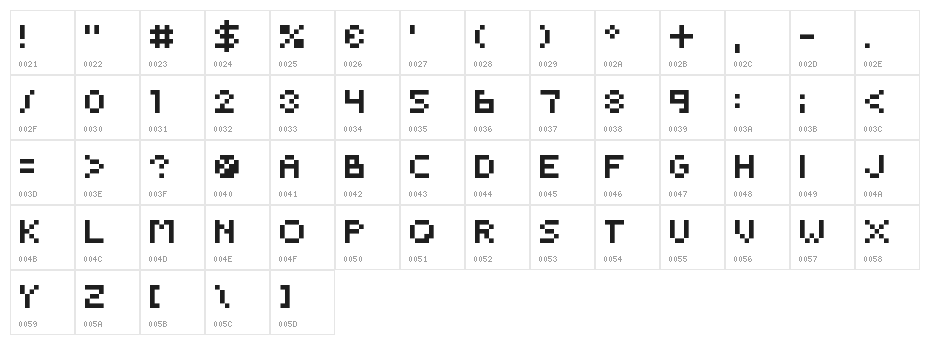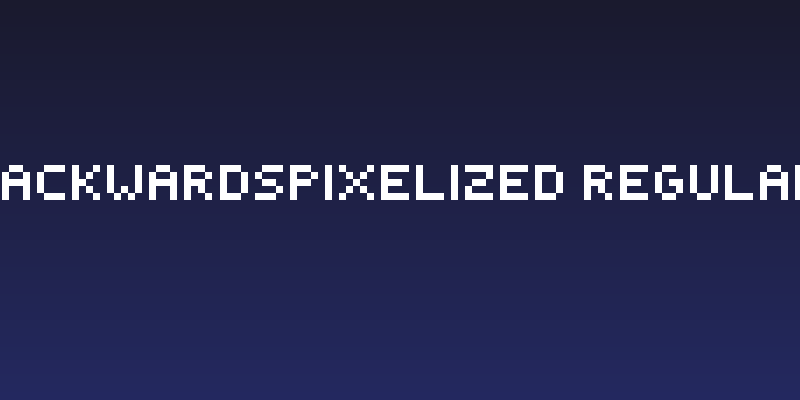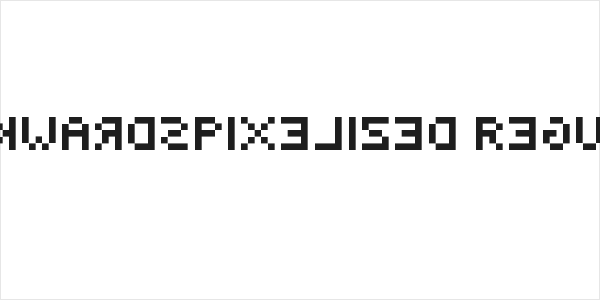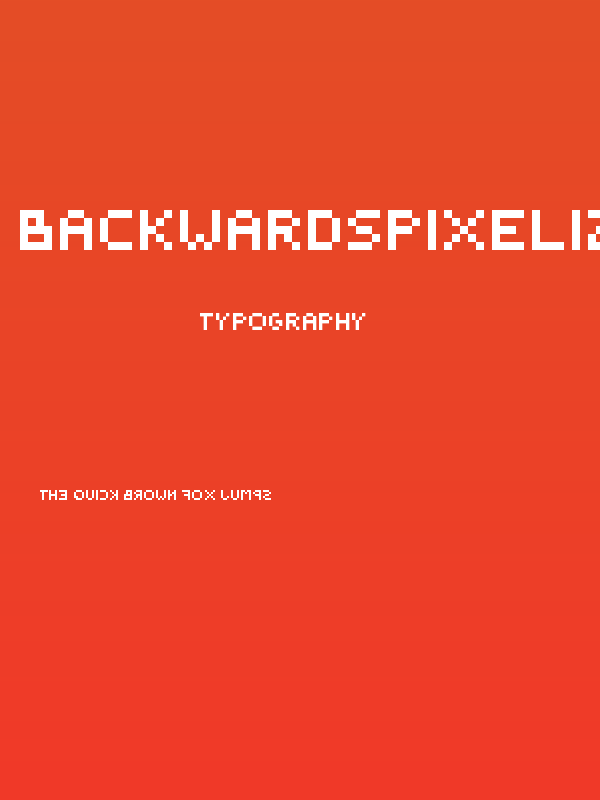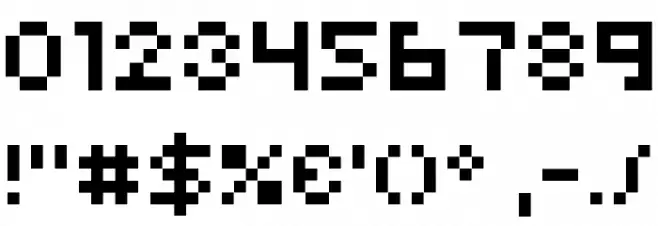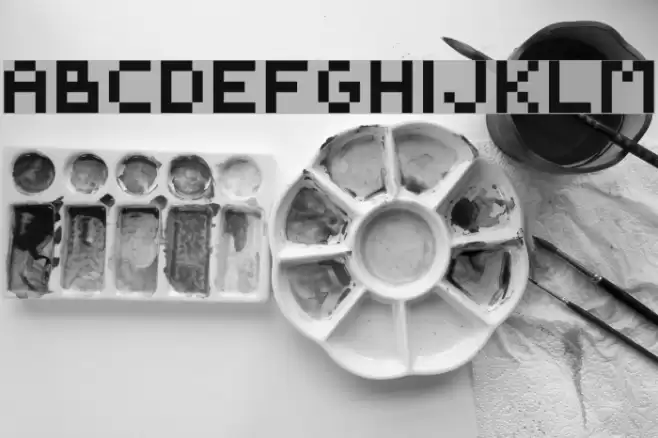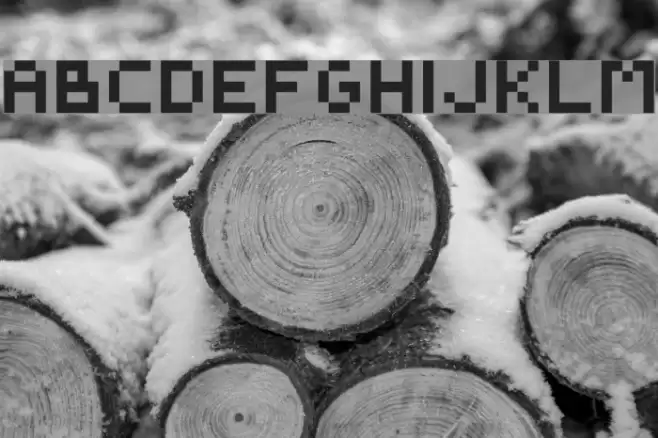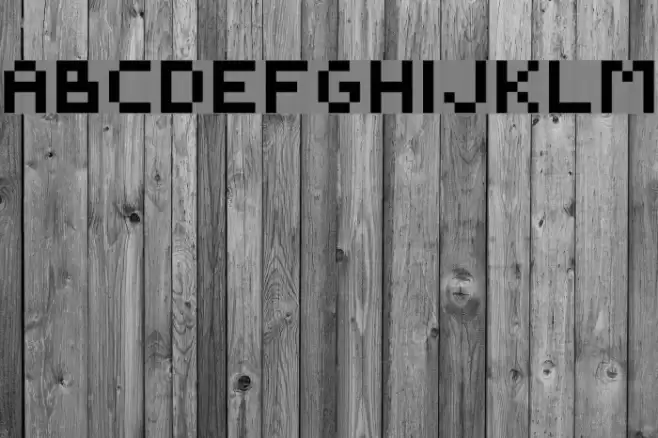
BackwardsPixelized Regular Font
| Kategorien | Pixel |
| Gesamtstil | Vintage |
| Anwendungsfall | Logos, Headlines, Digital Art |
| Vorgeschlagene Projekte | Ideal for video game design, retro-themed posters, digital art projects, and any creative work that requires a nostalgic digital aesthetic. |